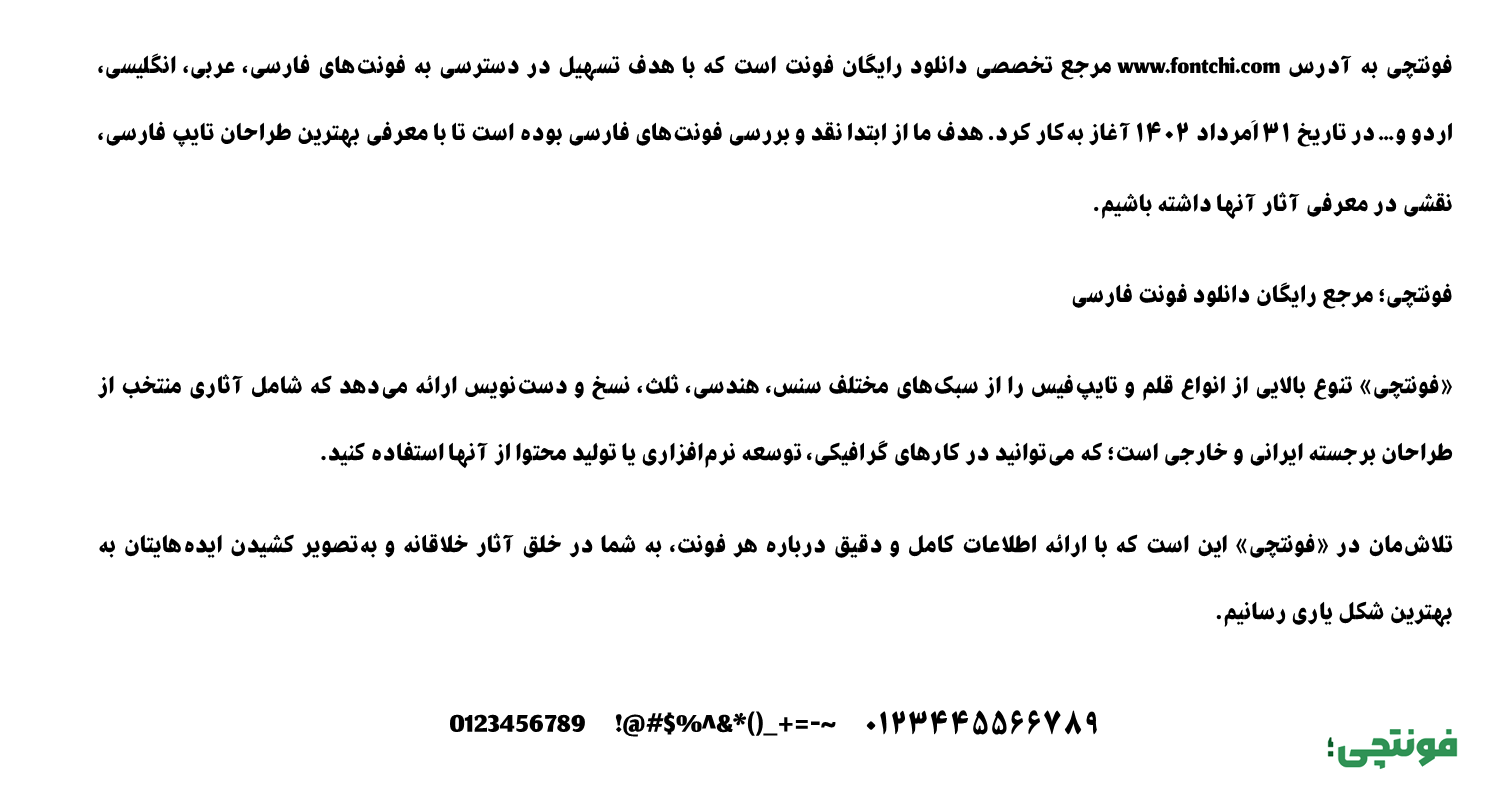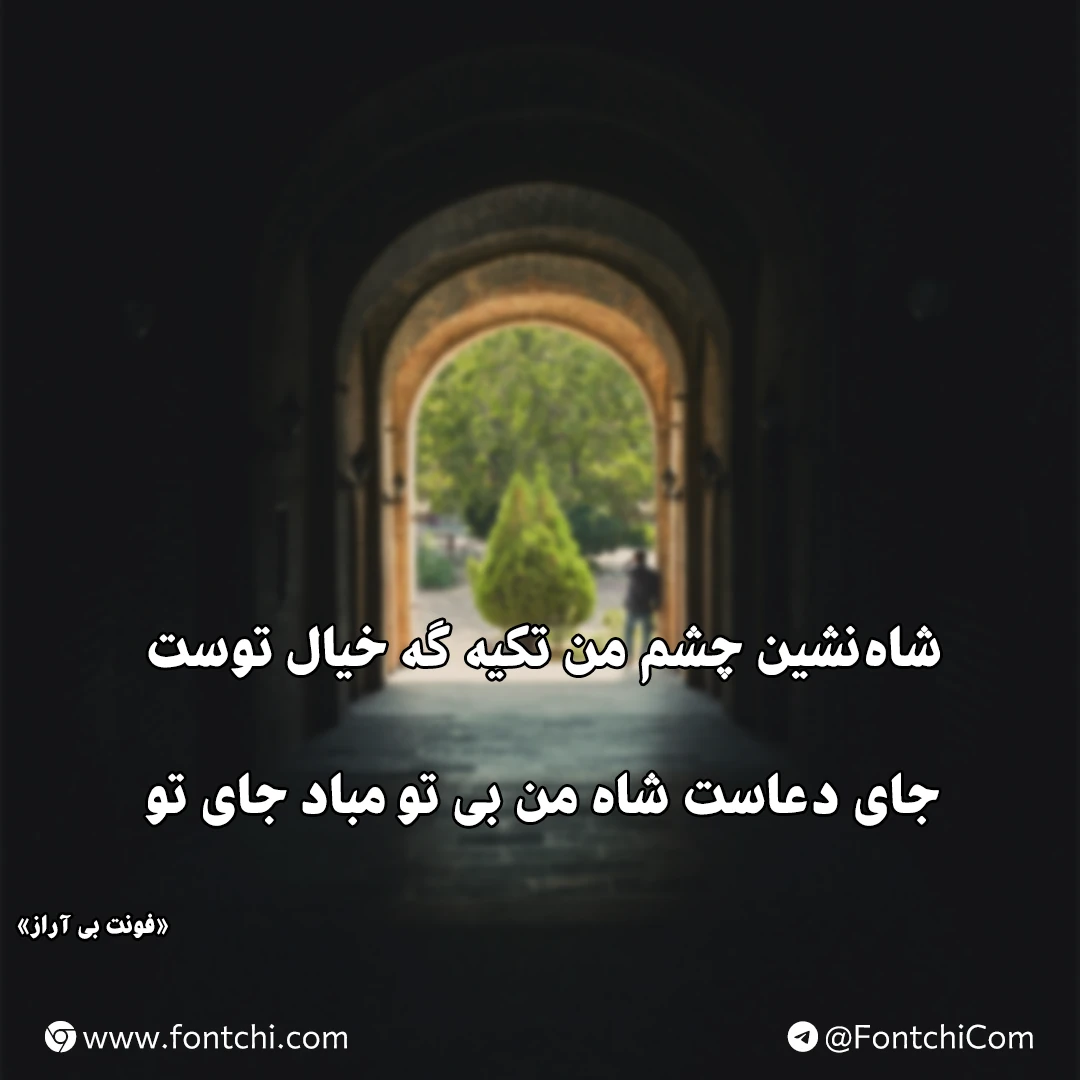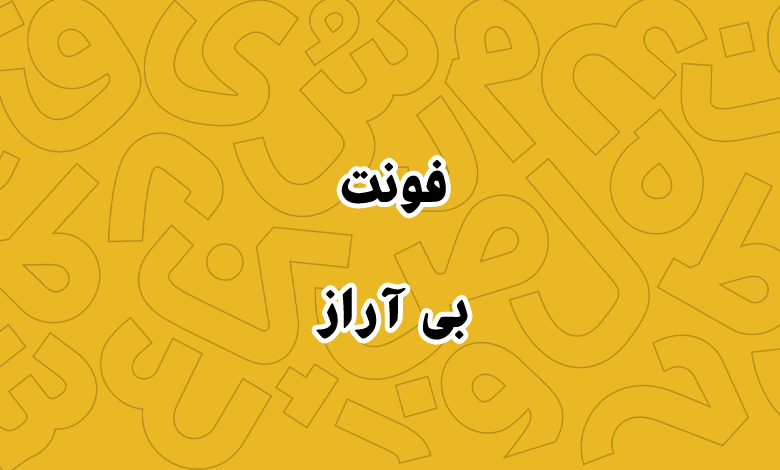
فونت بی آراز (B Araz)
فونت بی آراز یا آراز (به انگلیسی: B Araz) از سری فونتهای B با ظاهری بولد است که میتوانید از آن در متون کوتاه، عناوین و شعارهای تبلیغاتی استفاده کنید. این فونت با ظاهر فانتزی و خاص خود میتواند انتخاب خوبی برای متون نمایشی باشد.
محمدرضا شمس الکتابی این فونت فارسی را در سال ۱۳۹۱ در یک وزن معمولی (Regular) طراحی کرده است؛ اما ساختار فونت طوری است که بولد و سیاه بهنظر میرسد. این فونت با زاویه خاص و نسبتا ایتالیک در تمامی حروف طراحی شده است و همین ساختار آن را نمایشی کرده است.
تنها کاستی این فونت در بخش اعداد خود را نشان میدهد که فاقد اعداد عربی استاندارد «۴۵۶» است و به جای آن همانطور که در پیشنمایش بالا دیدید، از اعداد فارسی «۴۵۶» استفاده شده است. اما در مقابل اعراب و سایر کاراکترهای تزئینی حروف را پشتیبانی میکند.
این فونت برای زبان انگلیسی فاقد گلیفهای اختصاصی است و از فونت پیشفرض سیستم عامل استفاده خواهد شد.
همانطور که از ظاهر فونت مشخص است، برای استفاده در عناوین و متون نسبتا کوتاه مناسب است. از جمله آنها میتوان به موارد زیر اشاره کرد:
- فونت عناوین کتاب و مجلات بیشتر در موضوعات معاصر و داستانی.
- فونت پست شبکههای اجتماعی یا تامنیل ویدئوها در پلتفرمهای چندرسانهای.
- فونت تبلیغاتی برای طراحی تابلوها، بیلبوردها و پوسترهای تبلیغاتی محیطی سایز بزرگ.
- فونت عکس نوشته برای استفاده در شبکههای اجتماعی یا ساخت انواع کارت پستال.
این فونت از نظر سبک طراحی ظاهری نسبتا نزدیک به فونت گفته دارد. با این تفاوت که ساختار آن فونت هندسی تر است و از امکانات بیشتری برخوردار است.
یکی از کاربردهای این فونت در بخش وبسایت است. میتوانید با نصب آن روی سایت در بخشهای همچون اسلایدر یا عنوان نوشتهها از آن استفاده کنید. ظاهر بولد و سیاه این فونت موجب جلب توجه کاربران سایت شده و نرخ کلیک را افزایش خواهد داد.